Как определить шрифт по изображению: инструменты и ограничения
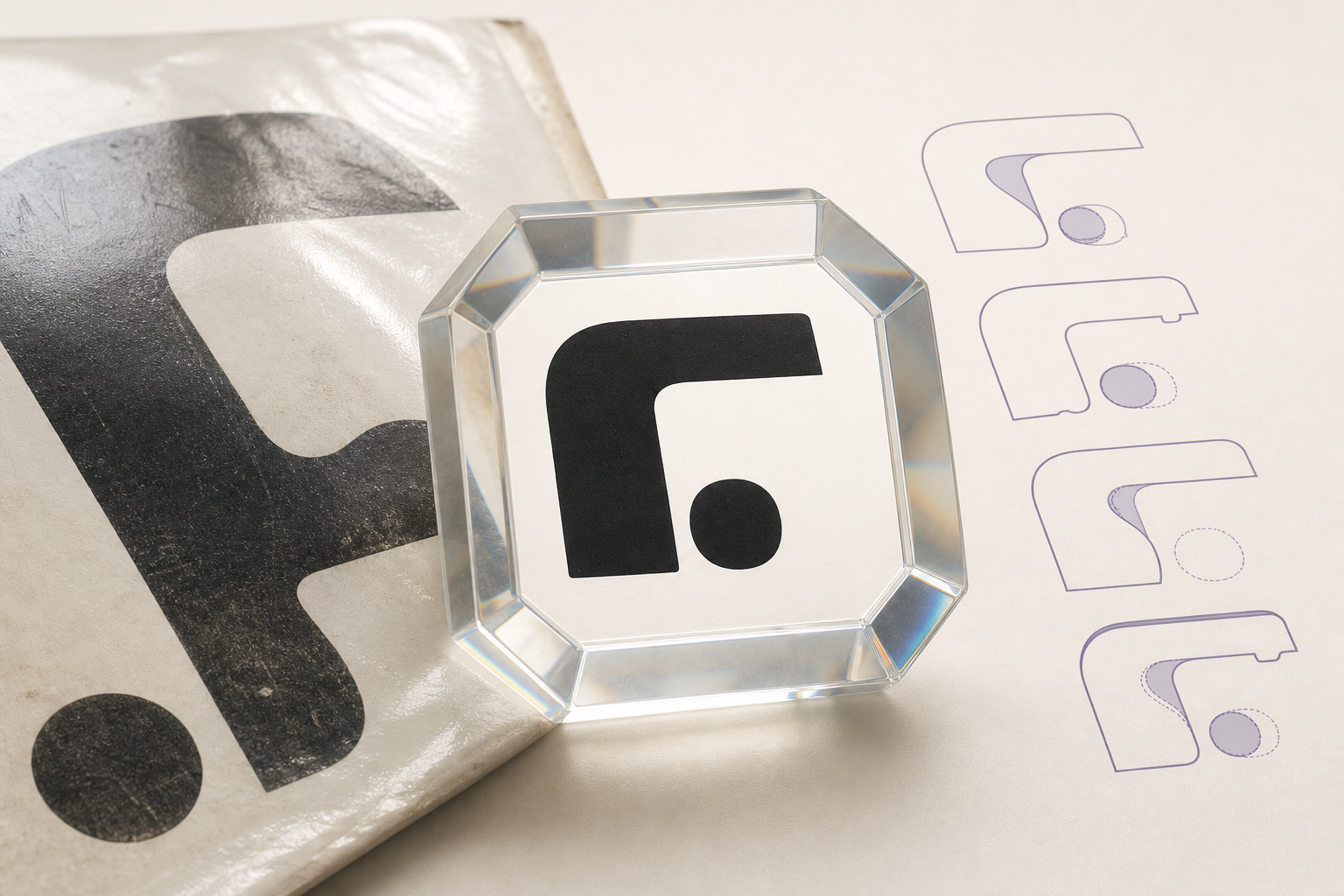
Определить шрифт по изображению можно через сервисы распознавания, поиск по каталогам и инструменты оптического анализа текста. Они сравнивают форму букв с базами гарнитур и предлагают наиболее похожие варианты. Точность повышается после обрезки, очистки и проверки отдельных символов, но точное совпадение невозможно гарантировать для логотипов и изменённых надписей.
Какие инструменты помогают распознать шрифт
Распознавание шрифта по картинке обычно выполняется не одним универсальным алгоритмом, а сочетанием нескольких подходов. Сервис выделяет текстовую область, анализирует контуры символов, учитывает их пропорции и сопоставляет результат с каталогом гарнитур. Поэтому полезно использовать разные типы инструментов: один быстрее находит визуальный аналог, другой лучше работает с текстом, а третий помогает проверить найденное семейство.
- Онлайн-определители шрифта принимают изображение и предлагают список похожих гарнитур.
- Каталоги шрифтов позволяют сравнить найденный вариант с образцами, начертаниями и языковыми наборами.
- OCR-инструменты распознают сам текст и помогают подготовить контрастный фрагмент для последующего поиска.
- Графические редакторы позволяют выровнять, обесцветить, увеличить и очистить изображение.
- Расширения браузера определяют шрифты на веб-страницах, но не всегда работают с текстом внутри изображения.
- Обратный поиск по изображению помогает найти исходный логотип, макет или страницу, где могла быть указана гарнитура.
Онлайн-сервисы сравнения гарнитур
К популярному классу инструментов относятся WhatTheFont, WhatFontIs и Font Squirrel Matcherator. Пользователь загружает фрагмент, сервис выделяет символы и показывает похожие варианты. Такие решения особенно удобны для латинских надписей на чистом фоне. Результат следует воспринимать как подборку кандидатов, а не как доказательство того, что найден именно исходный файл шрифта.
Каталоги и визуальное сравнение
Если автоматический поиск не дал убедительного ответа, помогает ручное сравнение. В каталоге нужно проверить форму строчной «a», верхней «G», цифр, знаков препинания, соединений в курсиве и характерных деталей засечек. Две гарнитуры могут выглядеть почти одинаково в слове из пяти букв, но заметно отличаться в расширенном алфавите.
OCR и графические редакторы
OCR не всегда определяет название шрифта, потому что его основная задача — прочитать содержание изображения. Тем не менее распознавание текста помогает отделить буквы друг от друга, понять язык надписи и получить чистый фрагмент для сервиса идентификации. В редакторе можно повысить контраст, удалить фон, исправить перспективу и сохранить изображение в удобном формате.
Как работает определение шрифта по картинке
Алгоритм анализирует не название файла и не смысл слова, а визуальные признаки букв. К ним относятся толщина штрихов, ширина знаков, высота строчных, форма овалов, контраст между основными и соединительными линиями, характер засечек и расстояние между символами. Чем больше разных букв попало в образец, тем больше признаков доступно для сравнения.
- Выберите фрагмент, где надпись видна крупно и полностью.
- Обрежьте фон, декоративные элементы и лишние объекты вокруг текста.
- Исправьте наклон и перспективу, если изображение снято под углом.
- Повышайте контраст, но не превращайте тонкие детали букв в рваные контуры.
- Разделите символы, если сервис ошибочно воспринимает слово как одну форму.
- Загрузите несколько вариантов изображения и сравните повторяющиеся результаты.
- Проверьте кандидатов вручную на тех же буквах, цифрах и знаках, что есть в оригинале.
Какие изображения подходят для распознавания
Лучший исходный материал — прямой фрагмент текста без сильной компрессии, бликов и перекрытий. На скриншоте браузера буквы обычно сохраняют геометрию, а на фотографии вывески к перспективе добавляются тени, неравномерное освещение и искажения объектива. Если есть выбор, используйте исходный файл макета или изображение с максимальным разрешением.
- Выбирайте не одну букву, а слово или короткую строку с разными символами.
- Сохраняйте оригинальные пропорции букв и не растягивайте изображение без необходимости.
- Удаляйте фон, текстуры, тени, обводки и градиенты, если они мешают контуру.
- Избегайте фрагментов с рукописными соединениями, если буквы перекрывают друг друга.
- Проверяйте отдельно кириллицу и латиницу: похожие символы могут принадлежать разным наборам.
- Для фотографии вывески снимайте текст фронтально и при равномерном освещении.
Практические примеры поиска шрифта
Логотип с изменёнными буквами
Допустим, у вас есть логотип интернет-магазина на прозрачном фоне. Сначала выделите только буквенную часть и уберите пиктограмму. Затем загрузите вариант с чёрными буквами на белом фоне. Если сервис предлагает несколько геометрических гротесков, сравните ширину букв, форму окончания «t» и расположение точки над «i». Даже при совпадении основы логотип мог быть вручную отредактирован.
Инструменты определения шрифта по изображению хорошо подходят для первичного поиска, подбора альтернативы и анализа типографики. Максимально надёжный результат получается при сочетании качественного фрагмента, автоматического сравнения, ручной проверки и контроля лицензии. Если исходную гарнитуру не удаётся установить, ориентируйтесь на форму букв, ритм, ширину и общее настроение текста.